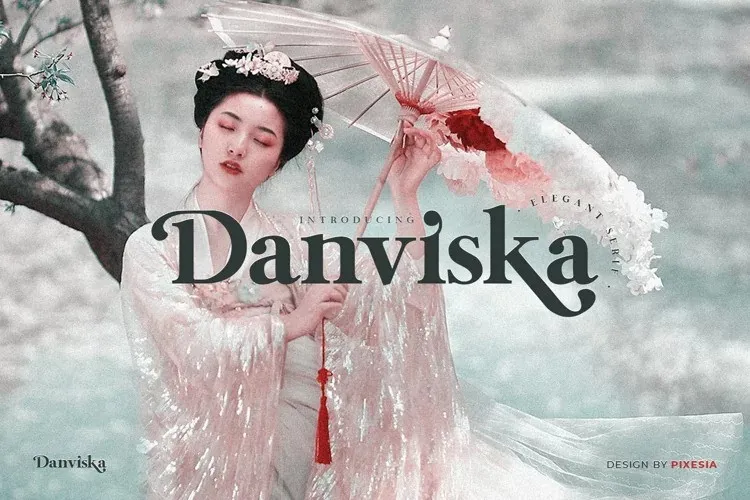
A Danviska Font é uma elegante serif que surpreende os olhos com suas curvas sofisticadas enquanto mantém sua classe inabalável. Lançada pelo designer Pixesia Studio, essa fonte PUA codificada oferece acesso fácil a todos os gílios e swashes. Suave mas poderosa, ela se destaca como uma escolha perfeita para quem busca elegância em cada layout. Crie designs épicas com o seu estilo versátil e impecável, fazendo deste um complemento perfeito para qualquer projeto. Seja você um designer ou criador de conteúdo, a Danviska Font é o gráfico perfeito que encanta os olhos.